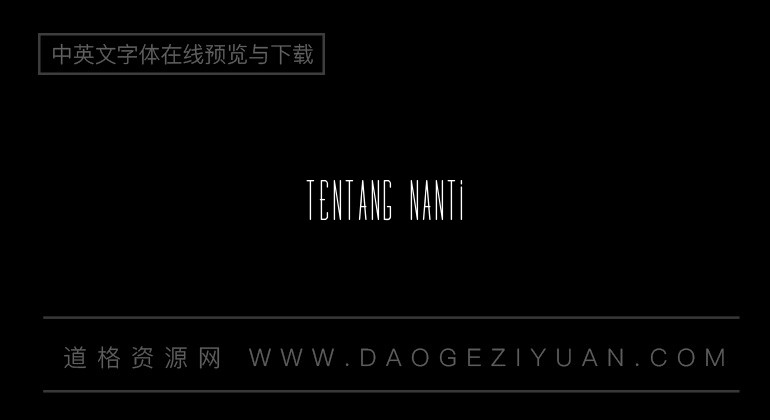
Tentang Nanti是一款免费的英文字体,由Indonesian设计师Rizka Maulana设计。它是一种细长的手写字体,采用更多的细线,使字体看起来更加精致。它有一种优雅的外观,可以用于报纸、海报、印刷品等不同的场景。Tentang Nanti字体可以帮助你创造出独特的设计,让你的作品更加精致。内容介绍
Tentang Nanti是一款非常不错的手写艺术字体,具有很好的视觉感,适合于文化类的宣传设计、商业类品牌的广告和产品包装设计以及个性化文字排版等较多场景。